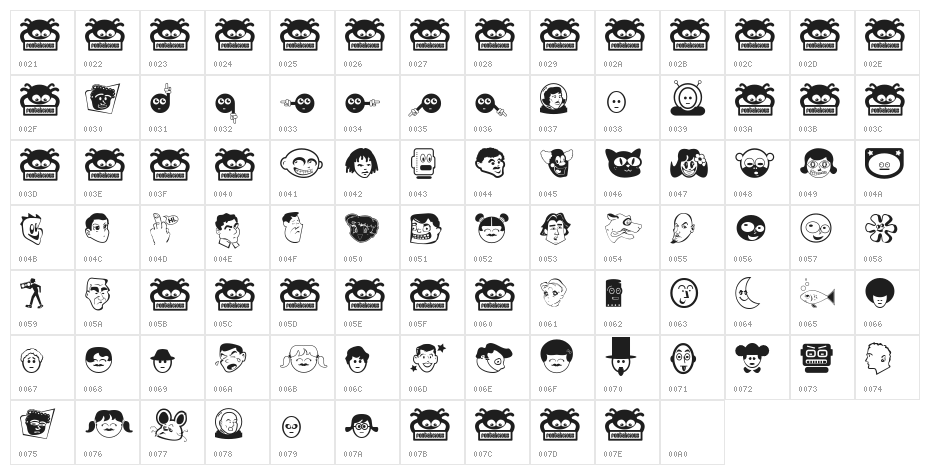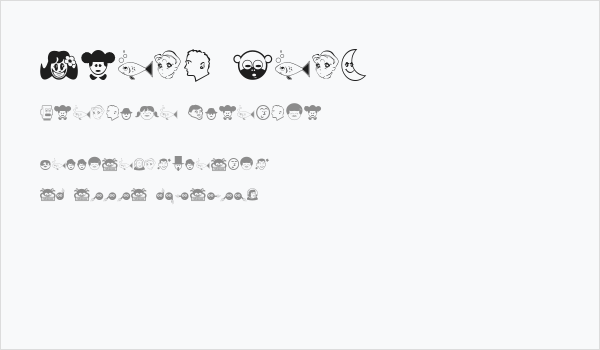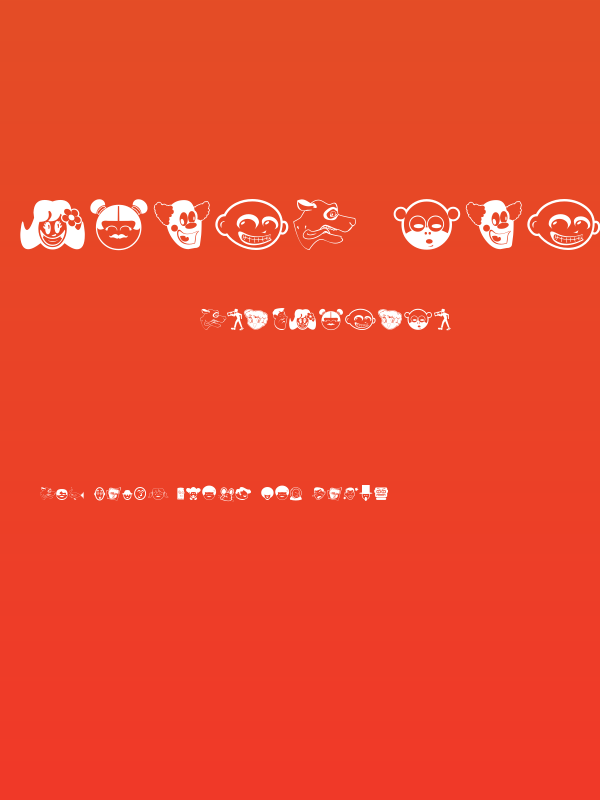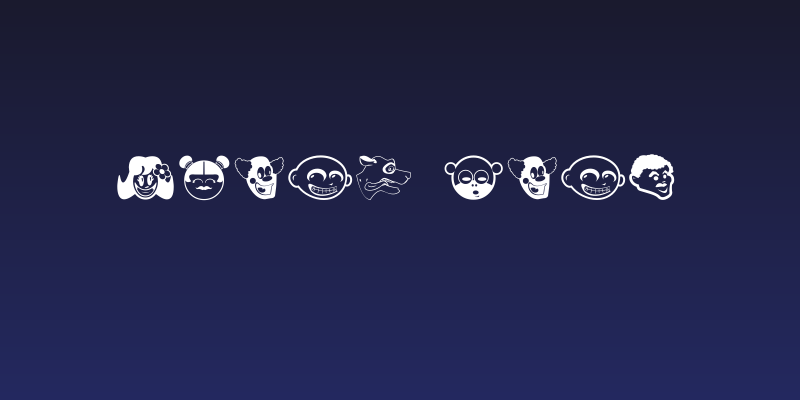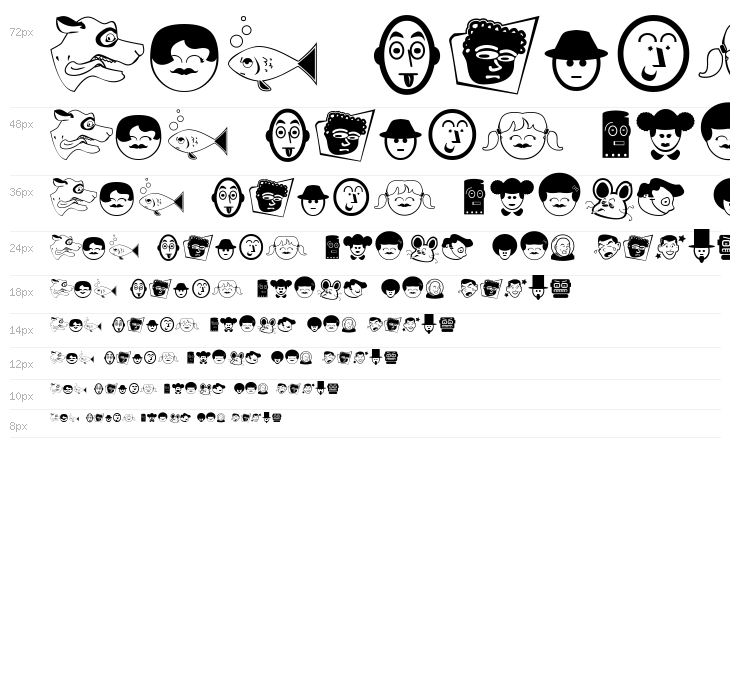
Great Head Font
| Stile generale | Playful, Whimsical, Cartoonish, Decorative |
| Caso d'uso | Icons, Decorative elements, Themed graphics, Informal projects |
| Progetti proposti | Children's books, comic strips, party invitations, playful branding, stickers, digital avatars, educational materials. |